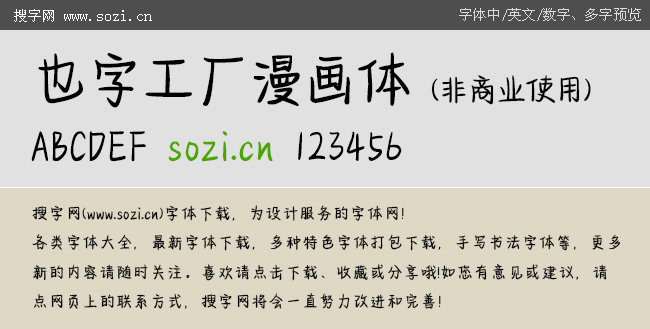
也字工廠漫畫體
搜字網(wǎng)給大家提供一款也字工廠漫畫體(非商業(yè)使用)中文字體下載,也字工廠漫畫體是一款手寫風(fēng)格的卡通字體,字體筆畫富于變化,使字體看上去更加生動,充滿趣味性,具有很好的視覺效果。適合應(yīng)用于兒童繪本、兒童海報、網(wǎng)頁設(shè)計等應(yīng)用(此字體為個人非商用版,商用可以聯(lián)系:官方網(wǎng)址:https://yefont.com/home,聯(lián)系方式:13798980448)。